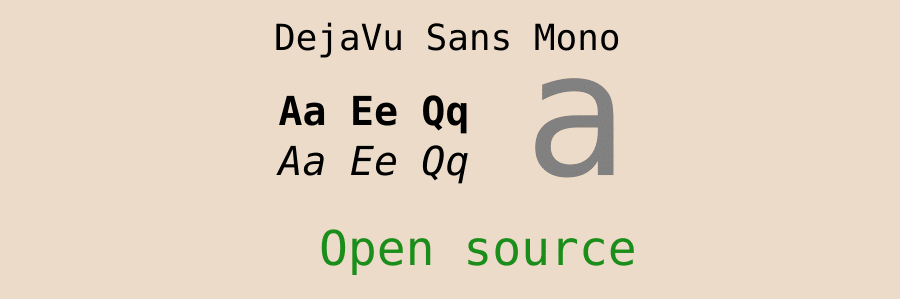
15种最佳编程字体以帮助您更愉悦地敲代码
经过几个小时的努力工作后,您是否感到眼睛疲劳或难以阅读代码?许多程序员在开始头疼之前从没想过要切换字体。
如果您经常发现在尝试扫描一千行代码时眼睛模糊不清,或者在停止编码数小时后头疼,那么可能是时候尝试一种新字体了。即使您没有遇到这些症状,设计良好的字体通常也比默认系统字体具有更好的可读性。
想把事情混在一起吗?很多这些字体都是免费的,所以尝试一下也无妨。以下是减轻眼睛疲劳和增强可读性的最佳编程字体,包括免费和付费。
为什么要切换编程字体?
IDE和开发人员工具并不总是附带最好的字体。通常,他们使用等宽系统字体,虽然它可能对某些人来说很好,但其他人报告眼睛疲劳或可读性差。
虽然这些程序中的大多数都提供了切换字体的能力,但许多人并没有利用它。一些程序员甚至可能没有意识到他们正在使用低于标准的字体,直到他们切换到社区支持的替代方案并意识到事情可以变得更好。
一个好的字体可以减少麻烦,让你的代码更容易扫描,甚至彻底改变你的工作方式。
那么合适的编程字体中有什么?这是您需要注意的事项。
• 在花费数小时查看数百行代码时,清晰易读的字符可减轻眼睛疲劳。
• 明确区分常见混淆字符,例如字母“O”和数字“0”或小写“L”和数字“1”。
• 流行编程语言中常用符号的连字或额外空格 – 不是每个人都喜欢,但其他人喜欢它。
• 对于某些字符的处理方式具有多种变体的字体非常棒,因此您可以准确选择您喜欢的版本。
许多程序员更喜欢等宽/固定宽度字体以提高可读性并使代码更容易扫描错误,因此它们中的大多数都属于该类别。如果您喜欢这种方式,其中一些包含捆绑的标准、非等宽版本。
免费编程字体
本着开源精神,许多设计师免费发布了他们的编程字体,其中大部分在GitHub等网站上。社区喜欢并推荐这些字体,因此请随时下载并查看它们。
1. Fira Code
Fira Code
Fira Code背后的概念很简单:等宽字体旨在将那些常用的多符号序列组合为一个,从而减少扫描代码并找到所需内容的时间。
例如,不等号 (!=) 变成带斜线的等号,HTML中的开始和结束符号(</) 间隔更近,依此类推。这些连字存在于许多编程语言中。
这不会改变任何底层字符本身,它们的外观,因此不会影响您的代码。它只是让阅读更容易!
还有一些字符变体,因此您可以根据自己的喜好微调字体。
大多数浏览器都支持Fira Code ,您可以在它们提供的真实代码示例中看到它的外观。
2. Proggy Fonts
Proggy Fonts
Proggy因其简单而有效的外观而受到开发人员圈子的喜爱,尤其是对于C和C++编码。您拥有常用的功能,如斜线零和有区别的字母以及额外的优化,如垂直居中的星号和轴对齐的算术运算符。
Proggy有多种变体,包括字体的矢量版本和十多个位图版本,这些版本改变了某些字符的呈现方式。选择您最喜欢的一个并开始编码!
3. DejaVu Sans Mono
DejaVu Sans Mono
DejaVu字体旨在涵盖整个Unicode 字符集,虽然该目标尚未完全实现,但其覆盖范围远比大多数其他字体提供的要广泛得多。
DejaVu Sans Mono也遵循这个原则,当然,它是适合开发的等宽字体。可读性和突出的字符使其成为程序员的不错选择。
4. Source Code Pro
Source Code Pro
Adobe已经在其Source Sans系列中发布了几种开源字体,其中一种是等宽字体,并且明确地为UI制作。尽管常规权重适用于大多数编程应用程序,但如果您需要,可以使用一系列权重。
虽然这种字体与Source Sans非常相似,但它进行了一些更改以更好地适应编码器:优化符号、点零、修改“i”、“j”和“l”等等。
5. Dina
Dina
Dina是一种清晰且设计简洁的字体,它使代码更具可读性并减少了令人头疼的问题。
此版本从原始版本重新制作,转换为TTF,并进行了更新以删除工件。与其他尝试不同,这可能是最高质量和最完整的转换。
如果您需要,还有一个粗体版本,如果您在重新制作时遇到问题,您也可以随时免费下载原始位图版本。
6. Terminus
Terminus
Terminus字体专为那些每天在编程终端中工作超过8小时的人而设计。它不会像其他字体那样伤害您的眼睛,并且非常易于安装和扫描。
自10多年前创建此字体以来,许多开发人员一直在使用它,因此它可能值得一试。
一些现代程序在位图字体方面确实存在问题,因此如果您遇到此问题,请尝试使用Terminus TTF。
7.Input
Input
如果您需要一种具有多种样式且在任何情况下看起来都不错的超级灵活字体,或者您在特定程序中不断遇到流行的位图字体问题,请尝试Input。
共有168种样式,您可以根据自己的喜好更换某些符号的字符默认值。您还可以调整行距。尝试在他们的网站上进行预览,看看它的多功能性。
该设计的灵感来自社区中流行的位图字体,并且对该过程给予了很多关注,包括将其制作成比例字体——尽管也可以使用等宽字体。
8. Hack
Hack
需要编码字体?Hack具有您可能需要的所有实用功能:粗体、斜体和两者的组合、电力线支持以及精心设计的字符以提高屏幕上的易读性。不再眯眼,不再头痛。
找到多语言编程字体可能具有挑战性,但Hack有超过1500个字形,所以这对于大多数语言来说都不是问题。
试用Font Playground以查看它在您最喜欢的编程语言中的外观,甚至将其与您系统上已安装的语言进行比较。
最后,尝试使用alt-hack和font-line工具来交换替代字符集并更改行距。
9. Cascadia Code
Cascadia Code
Cascadia Code是Windows终端和Visual Studio的默认字体。它包括默认、单声道(无连字)、斜体和草书字体,并且还额外支持嵌入电力线符号。
此外,该字体以其功能和风格的连字而闻名,尽管您可以选择启用没有这些的包。开发商的接受程度参差不齐;有些人讨厌它(或者更喜欢旧的默认设置,Consolas),而另一些人则喜欢它。
在任何情况下,它都是开源的,因此您可以自己尝试或启动Visual Studio以查看它的实际效果。
10. JetBrains Mono
JetBrains Mono
如果您使用JetBrains IDE,您可能对这种字体很熟悉。如果没有,那么您将想尝试一下。它专为开发人员设计,并针对阅读大量代码进行了优化。
JetBrains Mono包含近140个代码连字、8个粗体字,每个字重都带有斜体字,并支持145种语言。它也是开源的,可用于任何个人或商业情况。
11.Anonymous Pro
Anonymous Pro
Anonymous从90 年代中期开始有着悠久的历史,2001年为Macintosh开发的位图字体移植到TrueType。现在经典字体已被重新制作,您可以获得四种专门为程序员设计的固定宽度字体。
并非所有好的东西都是免费的,而且一些最好的编码字体是付费的。虽然您总是可以尝试使用开源字体,但您可能会喜欢这些字体中投入的额外精心设计、研究和工作。
12. Monolisa
Monolisa
厌倦了难看并导致眼睛疲劳的无聊等宽字体?Monolisa是一种独特的字体,它遵循等宽标准以减少疲劳,同时更令人赏心悦目。
除了为更好的阅读流程而设计外,Monolisa还包括电力线符号、200多种语言支持和几个连字,包括仅空格和整个符号替换。或者,如果那不是您喜欢的茶,您可以禁用它。
13. Gintronic
Gintronic
作为一名程序员并不意味着使用毫无生气的机器人字符集,“等宽”并不意味着“没有任何乐趣”。Gintronic既可读又美观,采用轻松而技术性的设计。
有六种样式,每种样式都有一个斜体集,支持各种符号和语言,而且它都有一个足够令人愉快的设计,你可以将它用于非代码目的,没有人会眨眼。
14. Dank Mono
Dank Mono
许多编码字体是为小屏幕设计的,其中许多还没有针对大屏幕进行更新。Dank Mono是个例外。它是专为高分辨率显示器设计的现代美学字体。
这当然不是您传统的位图等宽,但它做得很好,而且在做的时候看起来很棒。该字体在某些圈子中非常流行,并获得了普遍的好评。如果您想深入了解创作过程,请查看创作者关于他的设计选择的文章。
15. PragmataPro
PragmataPro